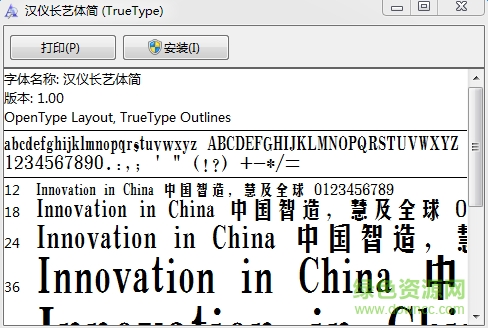
軟件介紹 軟件標簽: 漢儀字體 字體 漢儀長藝體簡是一款很好用的漢儀簡體字體,這種字體寫出來的字是很大氣的,而且一筆一劃都是那么的整齊,所以用于書本印刷、廣告設計等方面是很不錯的,歡迎有需要的朋友來綠色資源網(wǎng)下載。安裝說明:方法一:控制面板/字體/文件/安裝新字體;方法二:直接將字體復制到C:\WINDOWS\Fonts。方法三:針對win7系統(tǒng),用戶只需選中字體右鍵安裝即可。注意事項本站所有字體資源僅供個人學習與參考,如需商業(yè)使用請到相關官網(wǎng)授權。 本字體如果商用,請聯(lián)系漢儀字體官方獲得授權。 軟件截圖 上一張下一張(1 / 1) 安裝詳細截圖 其他版本下載 標題 大小 更新日期 下載 下載地址 電腦版 漢儀長藝體簡 點擊報錯 軟件無法下載或下載后無法使用,請點擊報錯,謝謝! 關閉報錯反饋 請描述您所遇到的錯誤,我們將盡快予以修正,謝謝! *必填項,請輸入內容 本類最新 漢儀孟瑞體ttf v1.0 官方版 漢儀字庫免費 132款 阿里巴巴普惠字體 官方ttf版 漢儀字體打包大全 for Mac 蘋果電腦版_ 共131款字體 漢儀純愛情書拼音體 ttf版 漢儀北魏寫經(jīng)w字體 免費版 相關文章 Photoshop字體安裝使用方法和技巧 如何解決“無法新增字體”問題 Win 7系統(tǒng)安裝字體方法 網(wǎng)頁字體大小設置方法 怎么改網(wǎng)頁字體大小 在Linux系統(tǒng)中安裝字體的幾種方法 windows7字體顯示問題:打開某些程序的時候顯示的是亂碼 用戶評論 熱門評論 最新評論 發(fā)表評論 查看所有評論(0) 昵稱: 請不要評論無意義或臟話,我們所有評論會有人工審核. 字數(shù): 0/500 (您的評論需要經(jīng)過審核才能顯示)